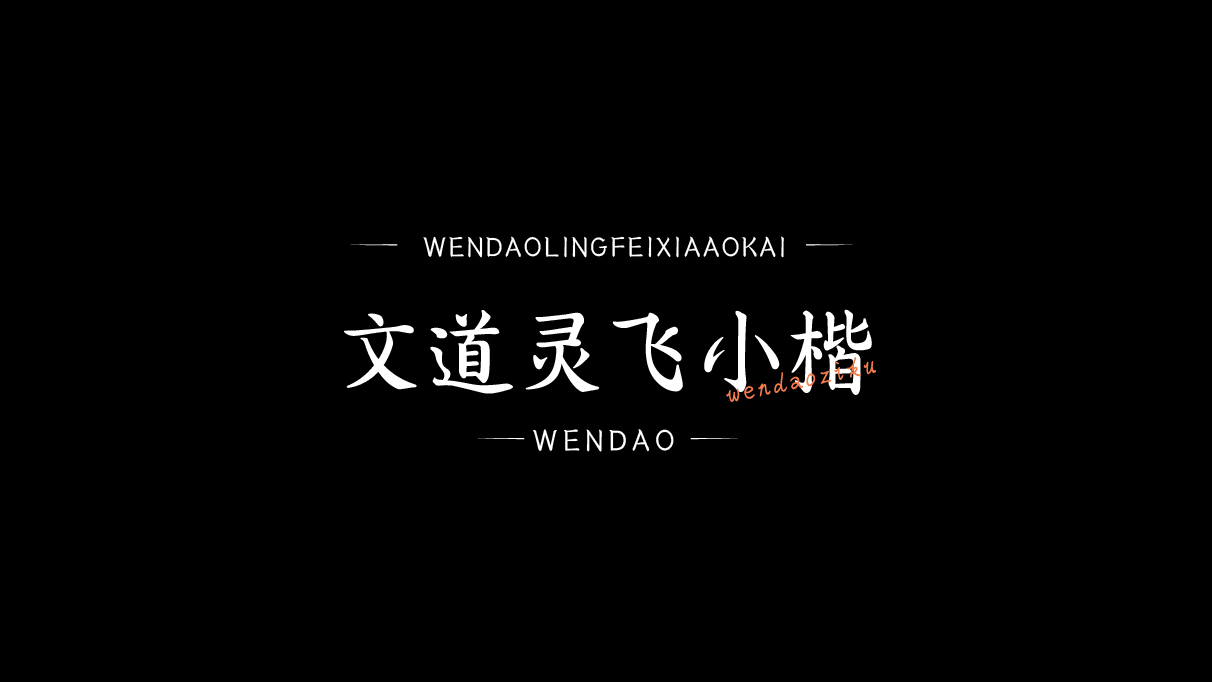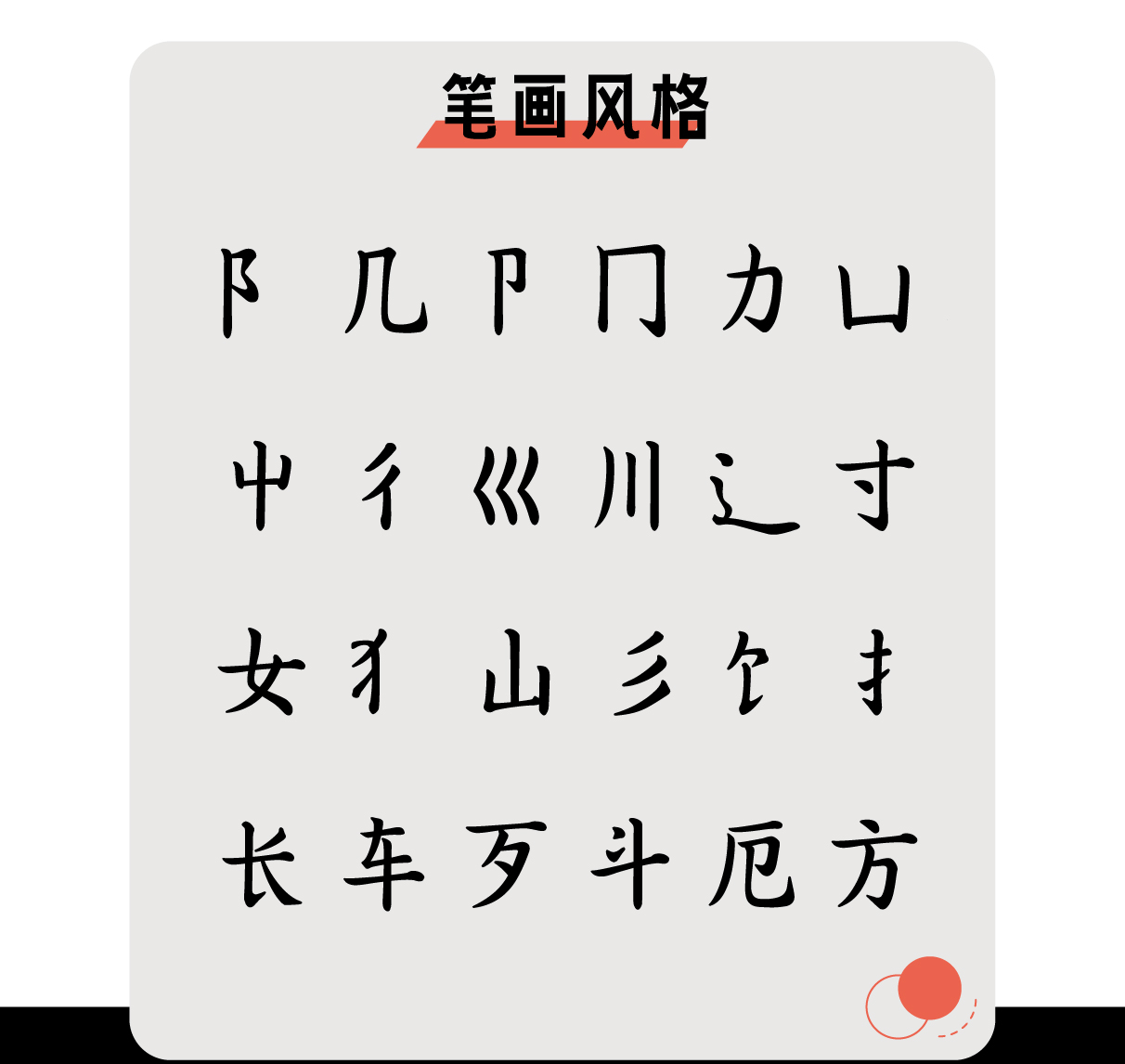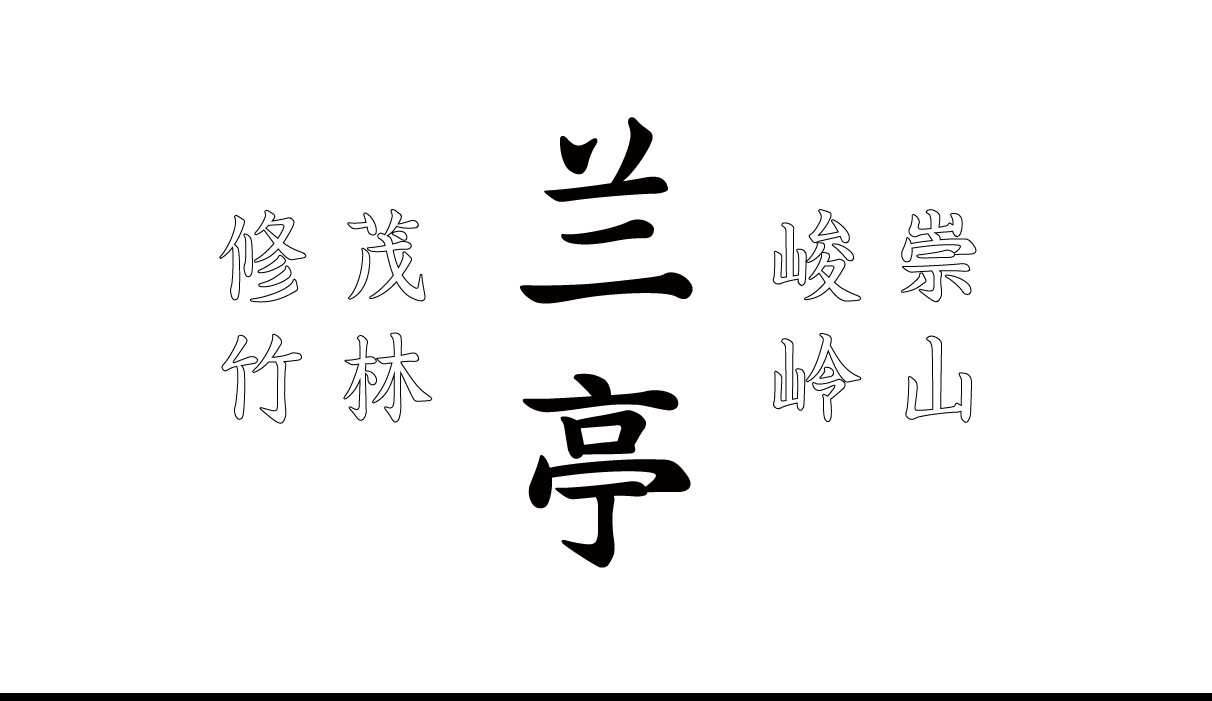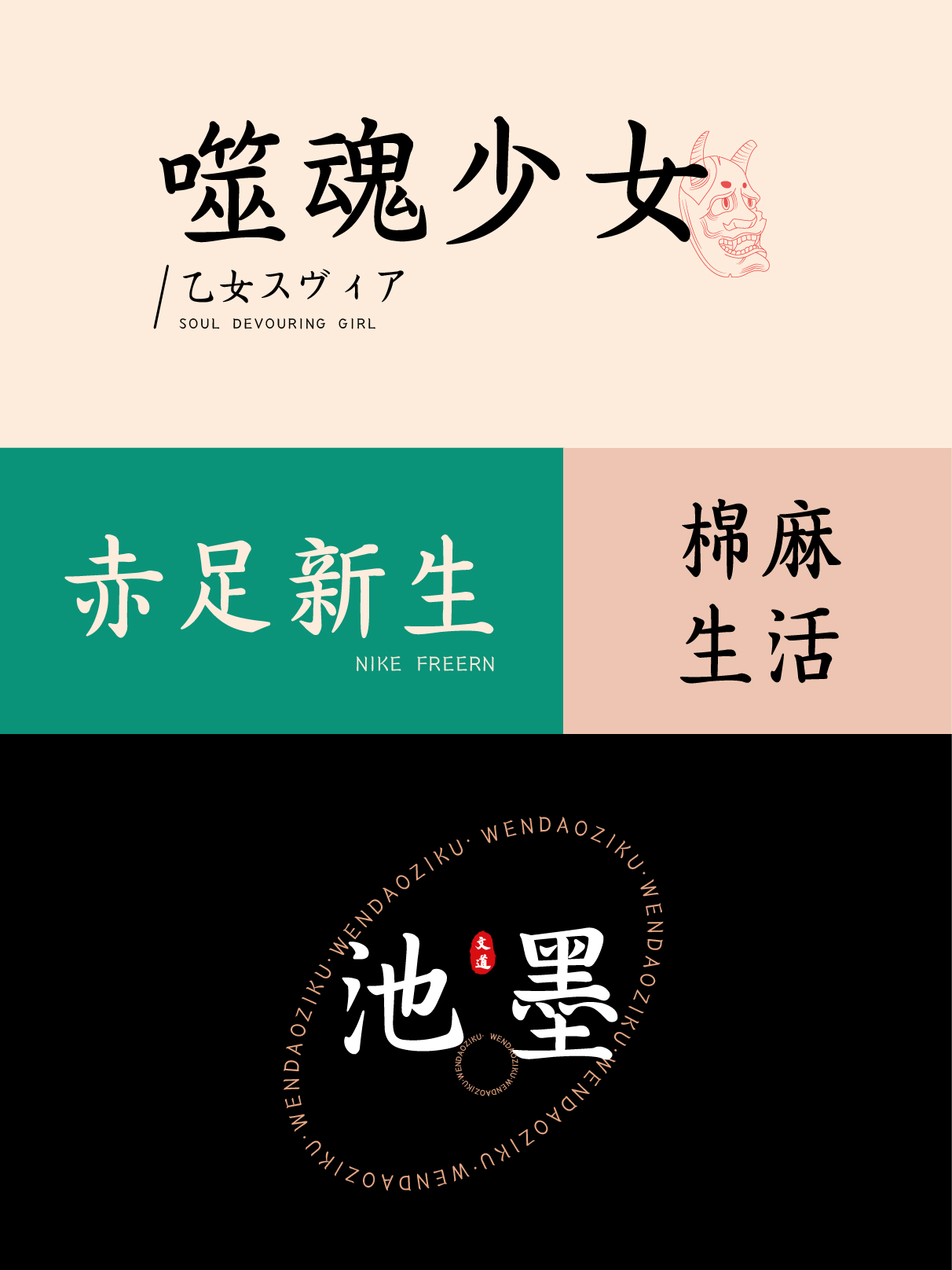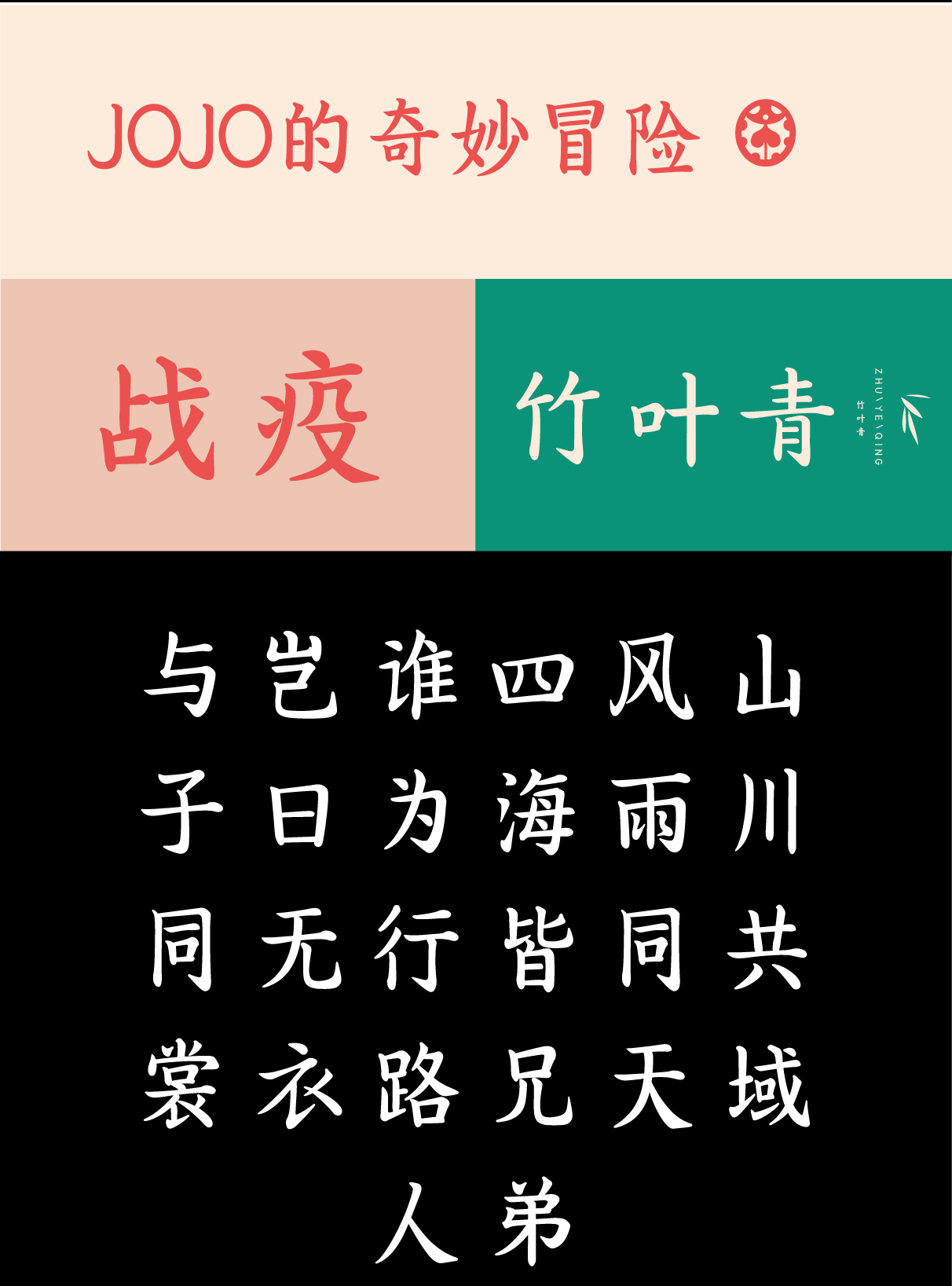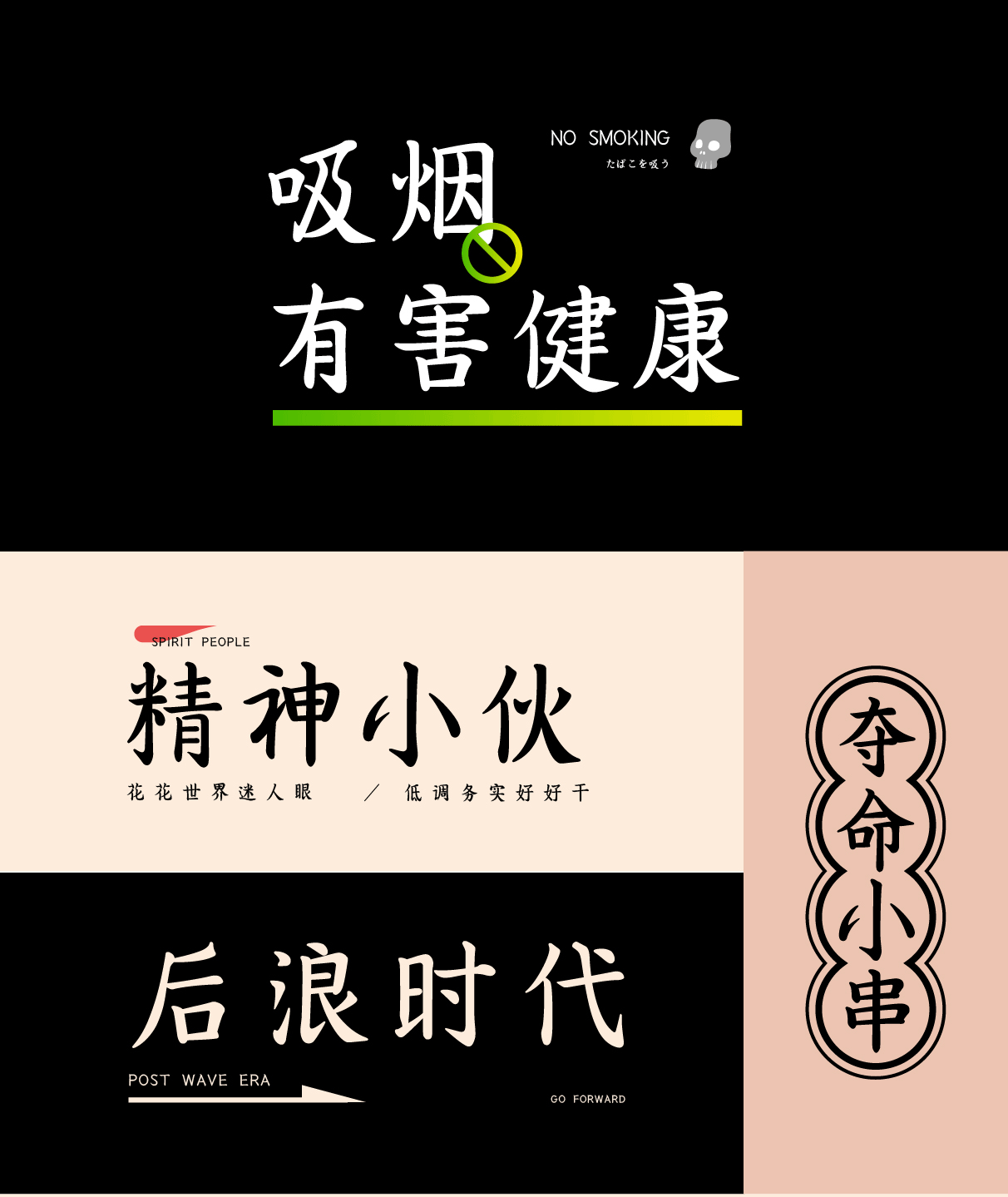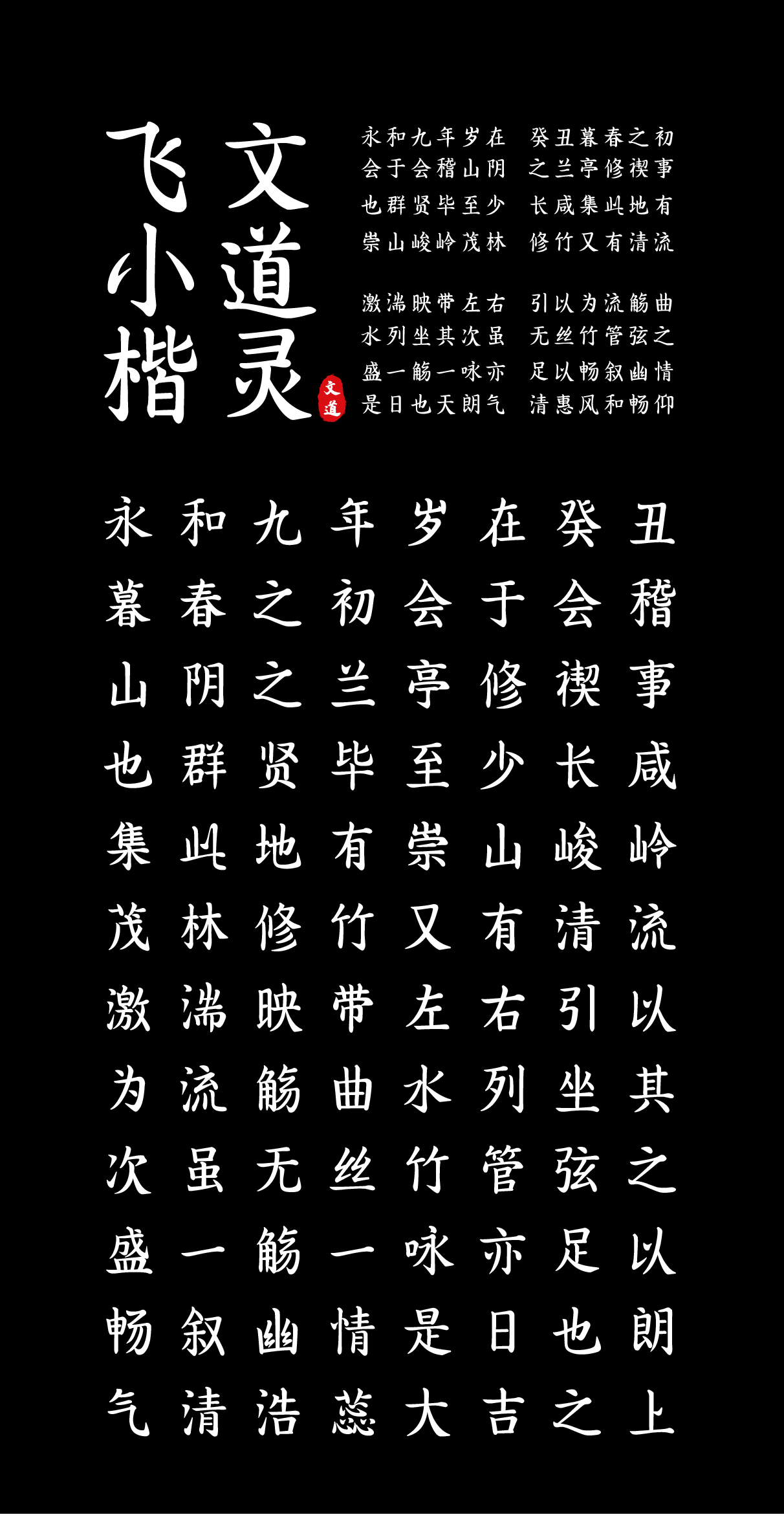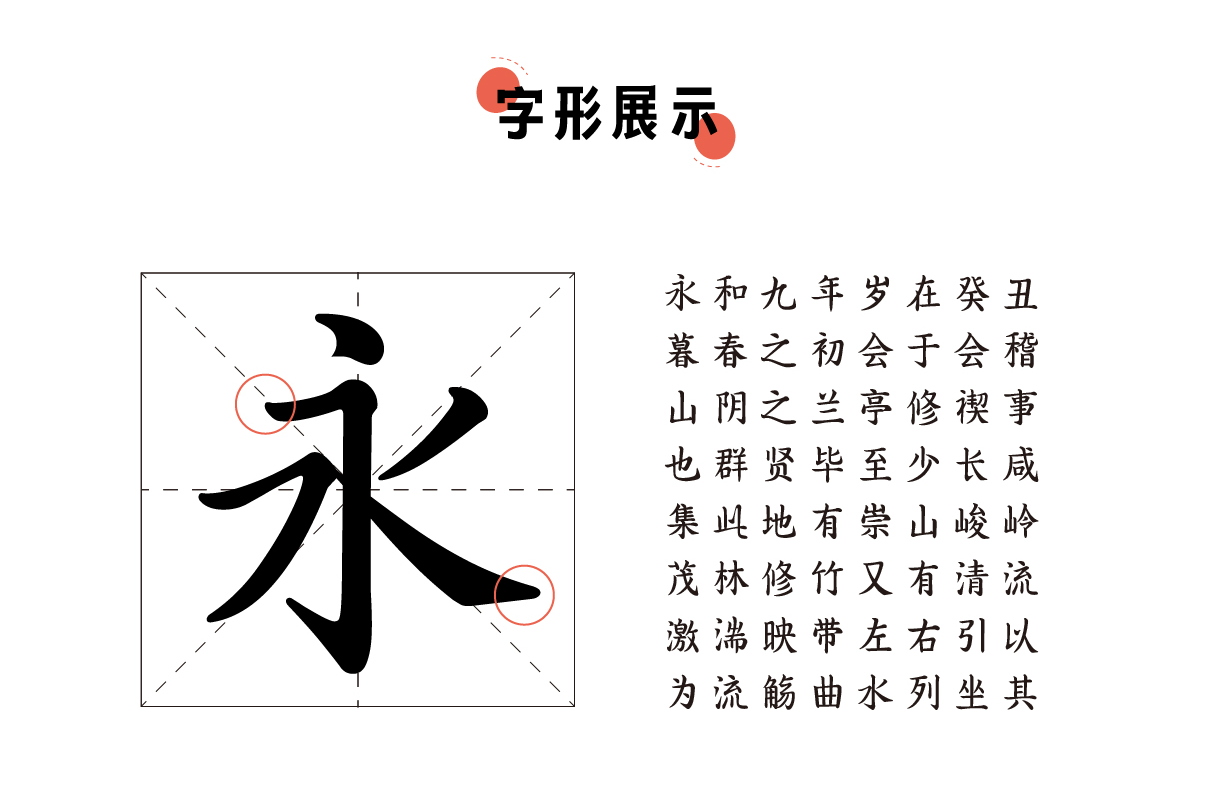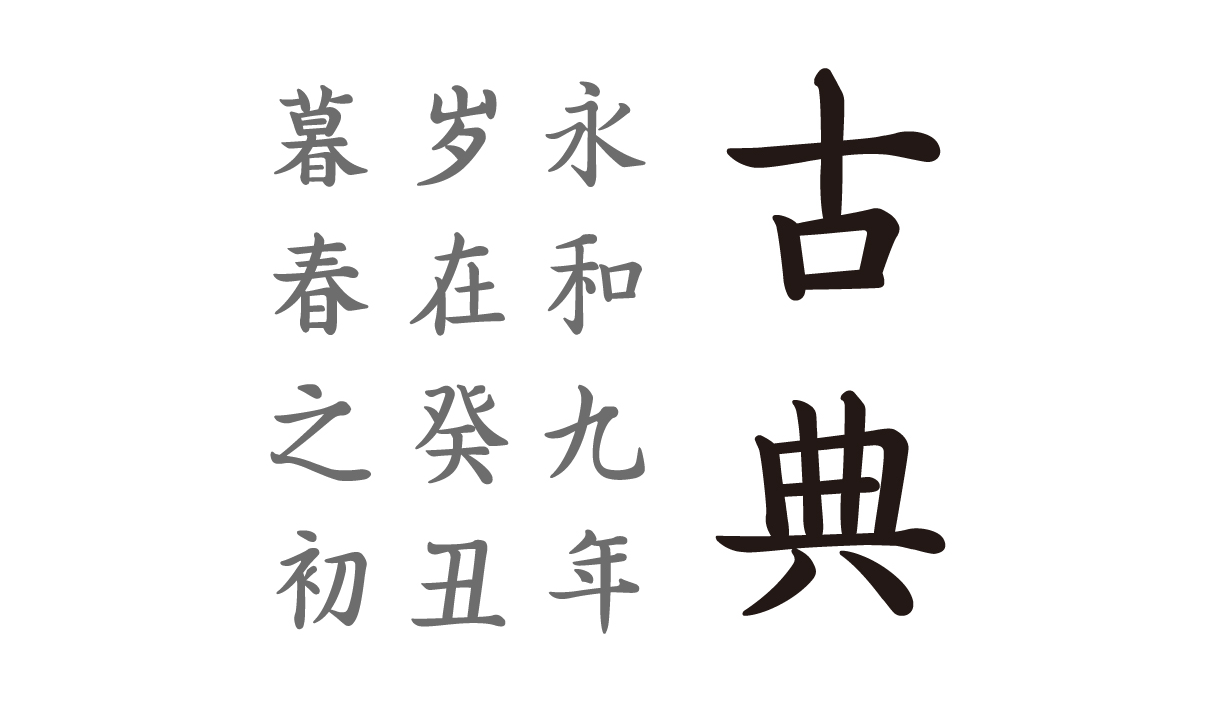
文道灵飞小楷
文亦有道,笔墨添香;墨韵飞扬,意蕴绵长。
字体名称: 文道灵飞小楷
所属分类: 楷体 屏显
适用场景: 广告 游戏 电商 新媒 综艺 影视 海报 印刷 包装
简介: 【文道灵飞小楷】该款字体以天下第一楷书《灵飞经》为灵感,笔画苍劲有力,结构端正平稳。适用于标题,书刊印刷,广告包装设计等场景。